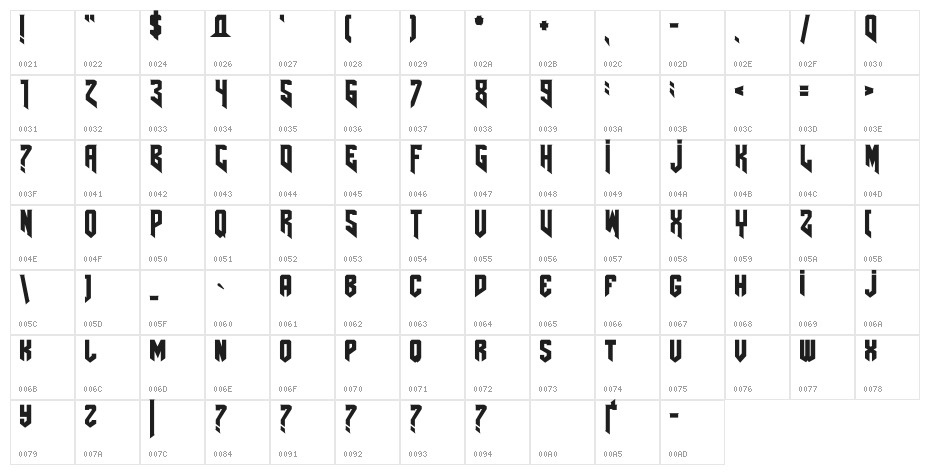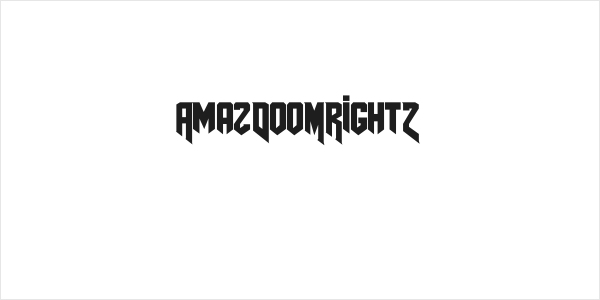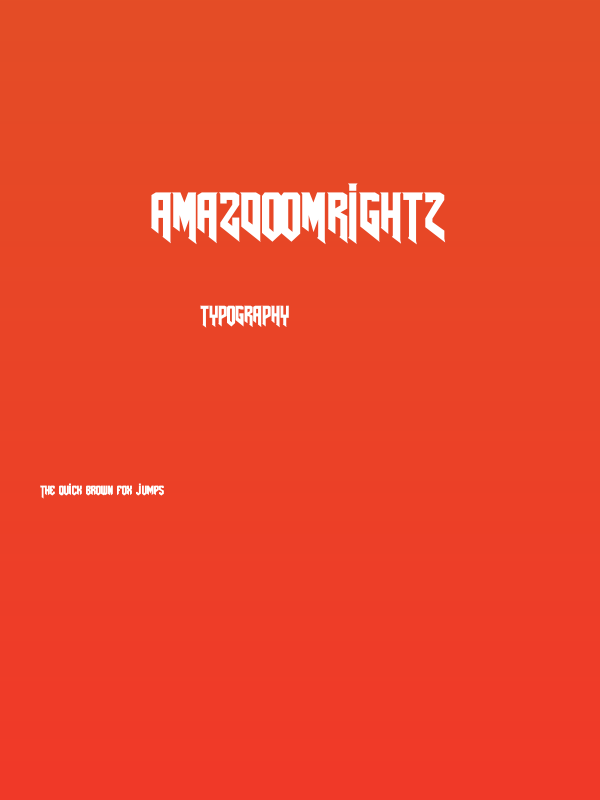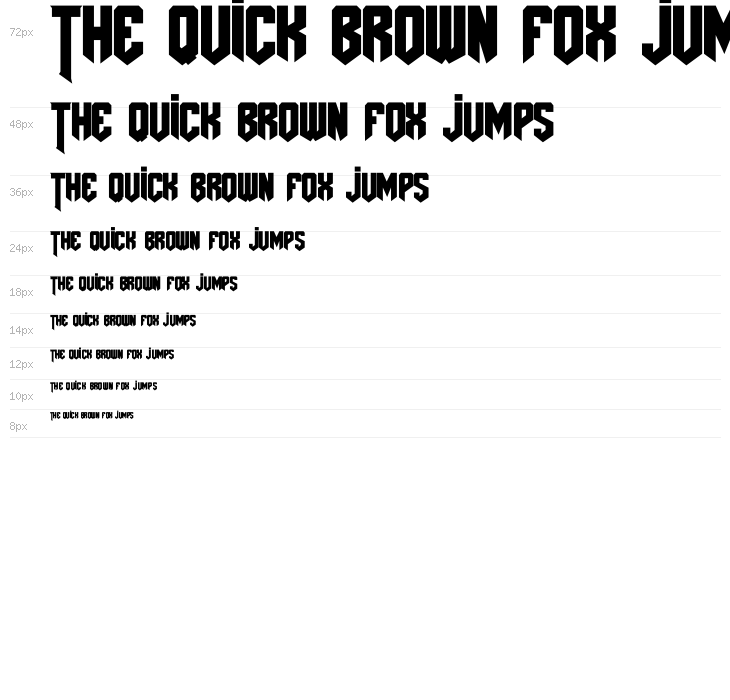
AmazDooMRight2 Font
| Progetti proposti | Ideal for video game titles, movie posters, branding for tech companies, or any project needing a strong, modern aesthetic. |